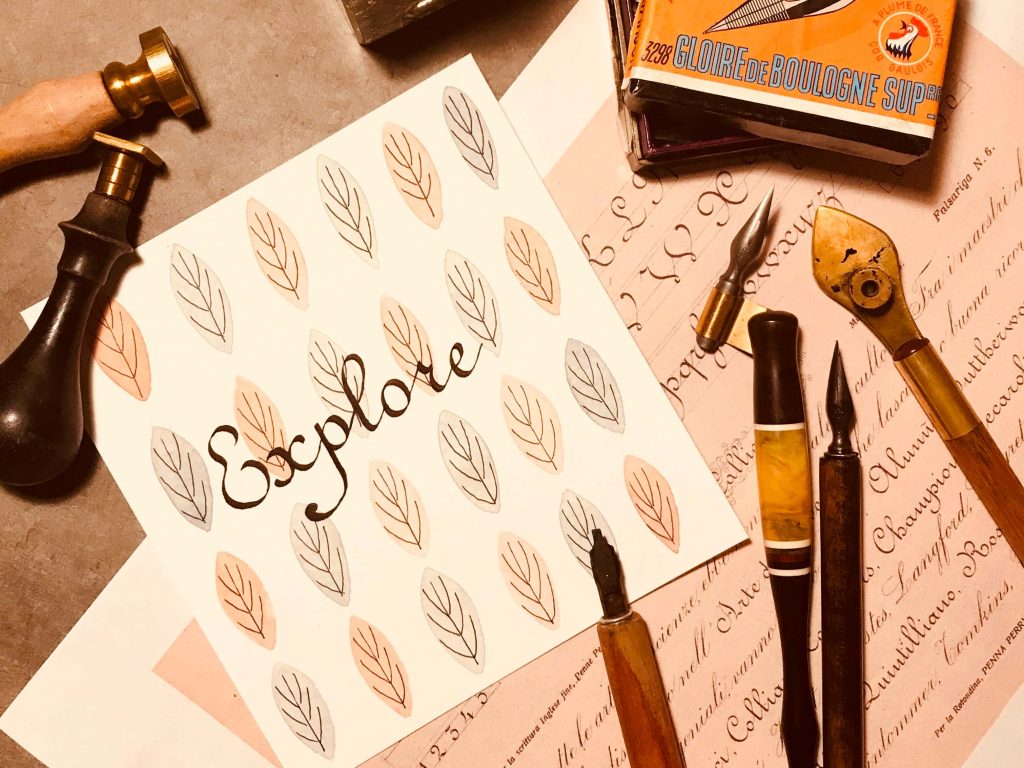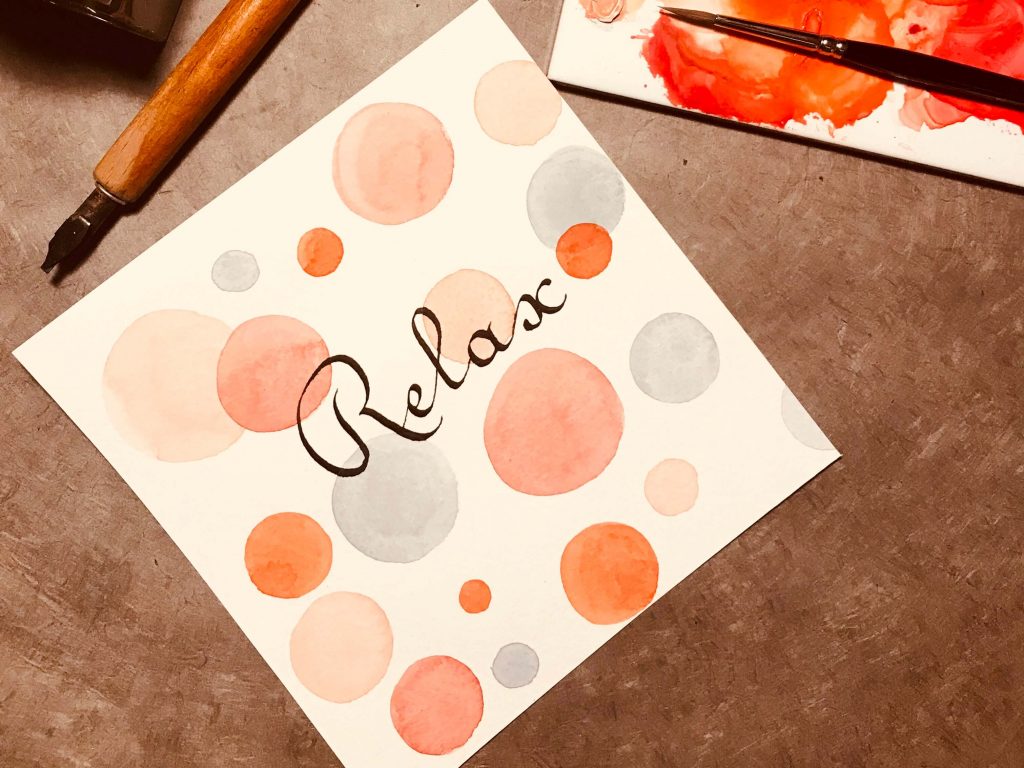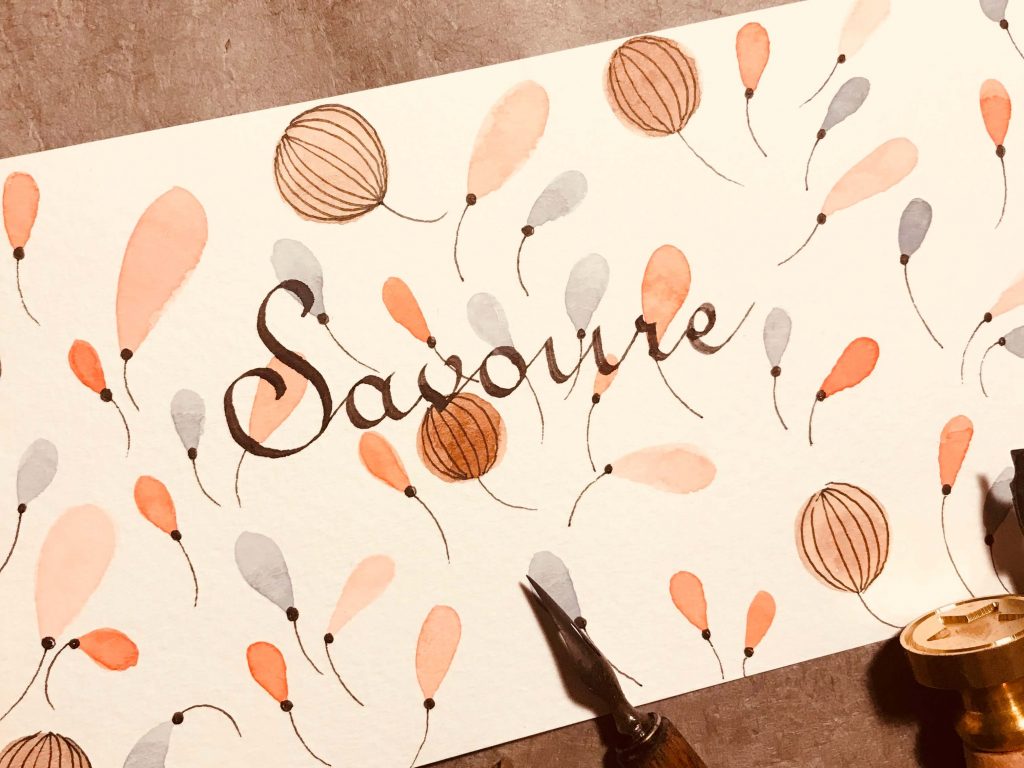
Si vous êtes sur cette page c’est que la calligraphie ne vous est pas totalement étrangère, du moins, qu’elle suscite votre curiosité. Si vous êtes sur le point de vous lancer et que vous doutez encore, voici 5 bonne raisons de prendre la plume, de découvrir et de pratiquer ! Passées les premières difficultés de prise en main, vous verrez que c’est un monde formidable qui s’ouvre à vous.
La calligraphie est une activité qui invite à la découverte
La grande variété des écritures, des outils, des médiums (encres, peintures, crayon…), fait qu’il y a déjà beaucoup de choses à découvrir et à expérimenter.
Quand vous faites de la peinture à l’huile… vous faites de la peinture à l’huile !
En calligraphie, vous allez redécouvrir le plaisir d’écrire, le pouvoir des mots, mais en plus tester de nombreuses façons de faire. Du coup, ce n’est jamais monotone car il y a toujours quelque chose de nouveau à explorer. Les possibilités sont infinies :
• Découvrir les différentes écritures
• Tester les supports, les matières, les couleurs, les outils
• Rechercher des textes
• Explorer les ressources historiques
Historique, contemporain, en couleur, en noir et blanc, riche/minimaliste : il y en a vraiment pour tous les goûts, toutes les saisons et toutes les humeurs !
La calligraphie est une activité relaxante
La pratique de la calligraphie associe le geste d’écriture, le calme, la patience, la concentration et la respiration. Chaque geste est effectué avec grand soin et lenteur pour atteindre la beauté de l’écriture. Ce travail procure un profond bien-être car il aide à se recentrer et à se réunifier intérieurement.
Le travail de la respiration en profondeur, notamment, aide a bien guider le geste.  Il aide aussi à se relaxer totalement, à travailler en pleine conscience, à s’isoler dans un temps suspendu où rien d’autre que votre geste ne compte. Tous vos soucis quotidiens sont mis de côté !
La calligraphie entraîne la concentration
La concentration est nécessaire pour bien former ses traits, ne pas oublier une lettre ou un mot en calligraphiant.  En pratiquant la calligraphie, on mobilise de profondes ressources intérieures. A force d’entraînement, la concentration se développe, se nourrit d’elle-même.
Ce pouvoir de concentration, la patience et le goût du travail bien sont bénéfiques au-delà de la calligraphie. Au travail par exemple, vous serez sans doute capable d’être plus efficace tout en étant moins stressé.e.
La calligraphie développe la créativité et la connaissance de soi.
Comme beaucoup d’activités artistique, le point de départ est une page blanche. Un mot, un vers d’un joli poème, une citation sont votre matière première. Votre maîtrise de l’écriture sera votre savoir-faire. Le reste du chemin – la composition – ira puiser dans les confins de votre imagination. La créativité est un processus qui se travaille, se nourrit dans le temps. J’en parlais d’ailleurs dans l’article sur les 100 fleurs. Avec vos mots, vos outils et vos couleurs, vous allez chercher à retranscrire une émotion. Pour cela vous allez chercher au plus profond de vous-même : qu’est-ce qui vous touche, vous affecte ? Qu’est-ce qui vous met en joie ? Quels sentiments voulez-vous exprimer ? Plus vous avancerez dans cette pratique, plus vous affirmerez un style qui vous est propre et qui correspond à votre sensibilité.
La calligraphie contribue à développer l’estime de soi
Réussir une belle composition, avec une belle écriture, est quelque chose de très gratifiant. En fait, la calligraphie demande pas mal d’entraînement, et c’est parfois un peu ingrat car on rate beaucoup de chose : écriture bancale, tâches d’encres, mots oubliés ou tronqués… Cela fait partie du parcours, on ne remporte pas un 100 mètre sans s’entraîner, hein ?
En revanche, vous serez amplement récompensés de votre travail et de votre assiduité. Vous développerez un savoir-faire qui suscitera aussi l’admiration de votre entourage, et vous recevrez beaucoup de compliments. Cet accomplissement fait du bien, pas pour l’ego, mais parce que vous aurez réussi à surmonter des difficultés et à créer quelque chose de beau.
En revanche, si vous prenez votre plume 3 fois par an et que vous ne fournissez pas les efforts nécessaires… rien ne se passera, et vous serez sans doute très frustré.e voire aurez le sentiment d’êtres nul-le.
Il y a une certaine justice, car au-delà des éventuelles prédispositions de chacun, c’est bien avec du travail que l’on arrive à un bon résultat !
Conclusion
Ne sortez pas votre petit kit de calligraphie tous les 29 février ! Osez-vous lancer, partez à la découverte et n’ayez pas peur de travailler régulièrement. Vous en serez largement récompensés.